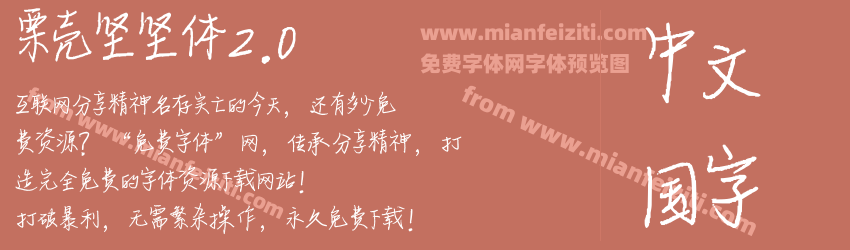
做一套字体,一直是我的梦想。
曾经,和多家大厂字体制作公司试稿,但都未通过。
究其原因,要么就是对字体不满意,要么就是他们的字库中已经包含类似风格的字体。
于是,我便想自己做一套字体。
24年8月,字体计划正式启动。这一套字体基于我自己的手写体来制作,按照GB/T2312-1980,共收录6763个汉字(附带数字、英文和标点符号等)。
9月,所有字体完成纸质稿书写,经扫描导入电脑,通过后期处理软件进行填充、切片,再通过专业软件进行制作,为保证字体间距合适、阅读舒适性等,还对所有的字逐一地进行了二次人工校对。
本款“栗壳坚坚体2.0”是一款书写很新颖的字体,字体大方,适合各种设计作品使用!欢迎下载!